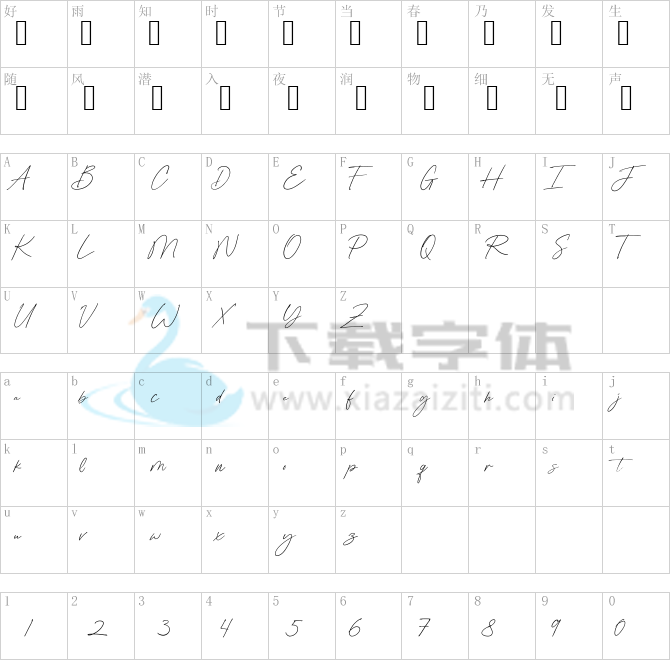
Amelia_Bloomer.ttf字体下载,这款字体结构工整、笔画清晰,兼顾美观与易读性,适用于标题、正文、海报、包装、LOGO 等多种场景。字形优雅稳定,风格百搭耐看,适配日常排版与创意设计,让文字呈现更舒适、更具质感。Amelia_Bloomer.ttf字体下载一笔一画,皆是细节,以均衡的比例、流畅的线条打造舒适视觉体验,字形端正大气,风格简约现代。无论是商业设计、品牌宣传还是日常排版,都能轻松驾驭,让文字更有格调与力量。Amelia_Bloomer.ttf字体下载字体下载。
Amelia_Bloomer.ttf图片展示